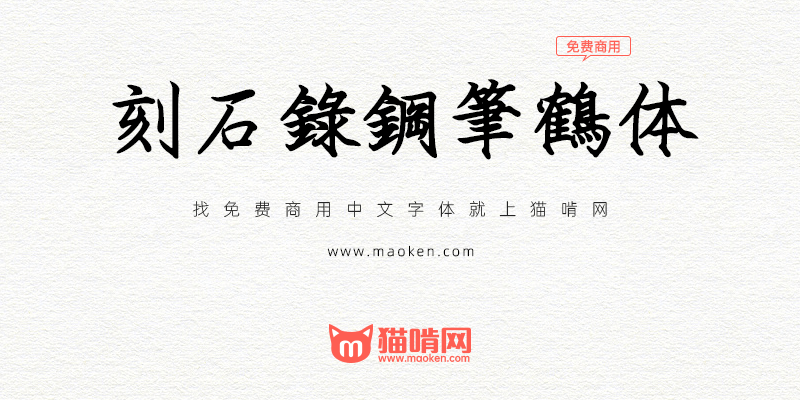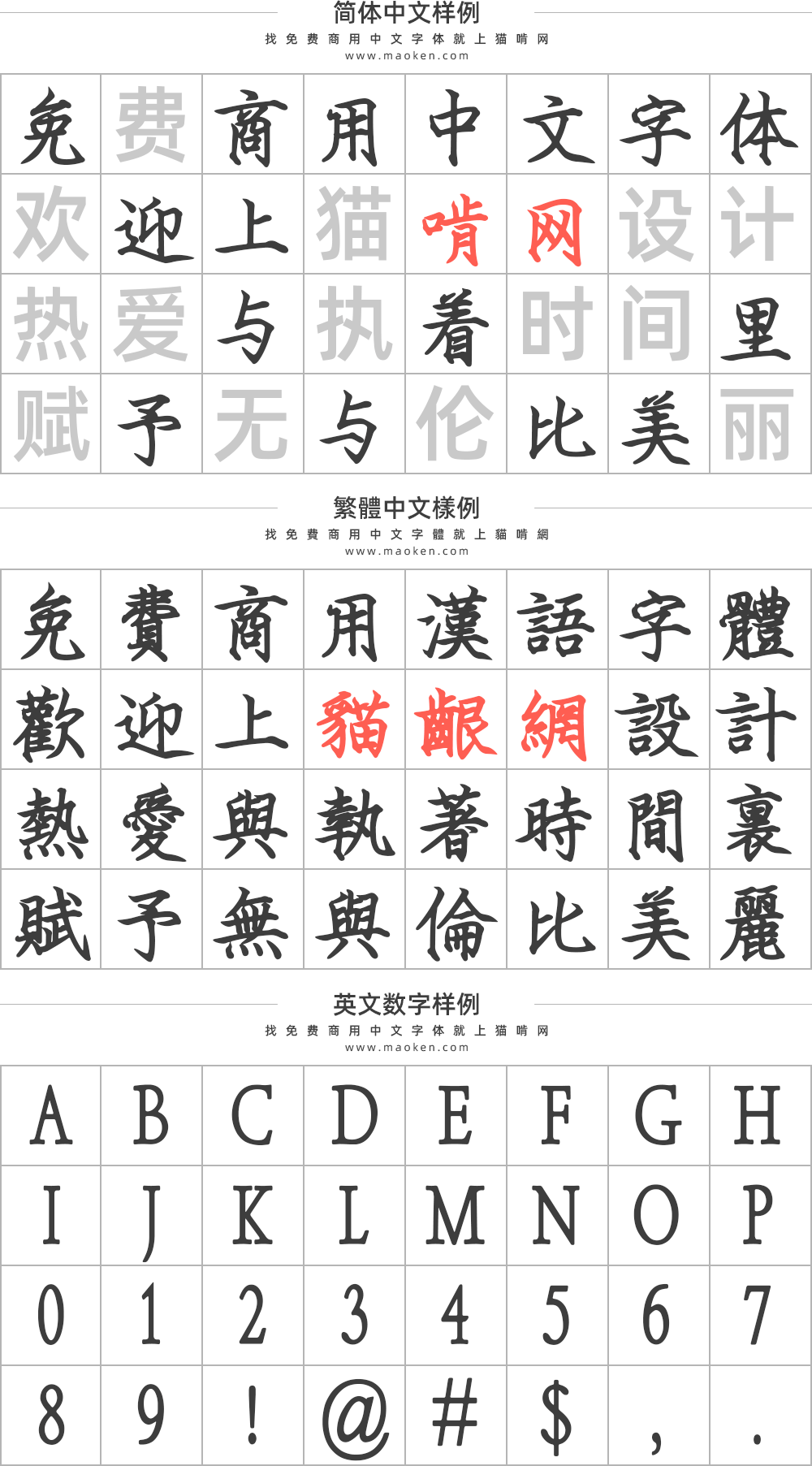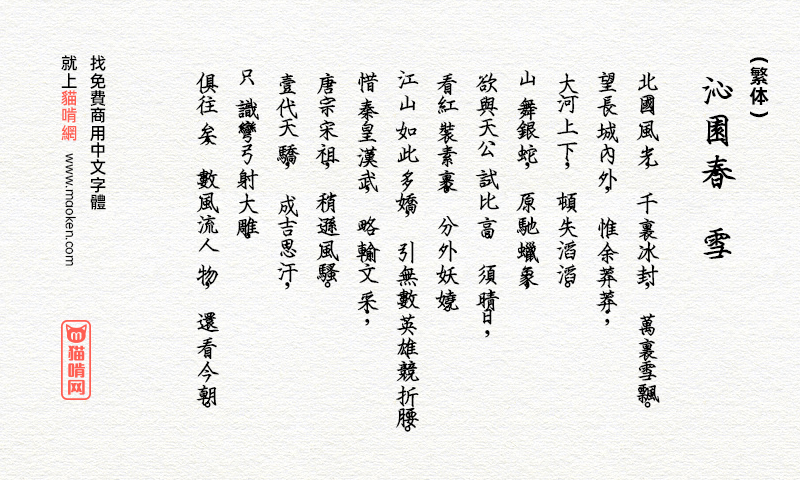
| PS字体名:I.PenCrane-B | 字体版本:Version 1.004(2014/07/07) 更新记录 |
| 字体作者:刻石录(中国台湾) | 字体字重:1个 |
字体特色
「刻石录钢笔鹤体」是一款非常不错的中文艺术字体,该字体笔画遒劲灵动,连笔张弛有度,结体清丽优美,整体效果很不错,能够适用于艺术设计、包装印刷、签名设计、图形设计等领域。「刻石录钢笔鹤体」选择了王汉宗粗钢体,重新制作和修整原字型中缺少的或有欠美观的部份,例如半角英数、圈圈字、常用符号等。